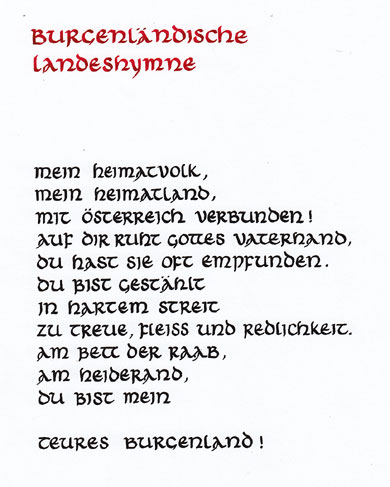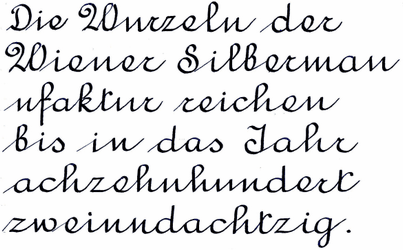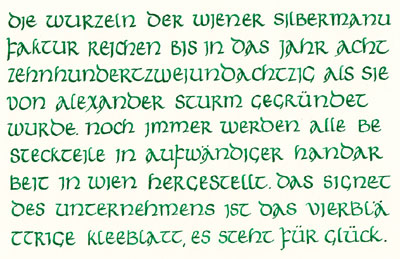
| Das Layout,
also der Gesamteindruck einer Seite, eines Plakates oder einer
Webseite, umfasst das Zusammenwirken von Text und Abbildungen. Die Typografie hingegen widmet sich nur den Textelementen, vom Buchstaben über das Wort, die Zeile und den Satz bis zum Textblock. Großbuchstaben (=Versalien) und Kleinbuchstaben (=Gemeine oder Minuskeln) werden mit bestimmten Abständen (=Laufweite) aneinander gereiht. Bei zu geringen Buchstabenabständen ist der Text schlecht lesbar, sind die Abstände zu groß, wirkt der Text löchrig: Hier ist die Laufweite zu klein, die Lesbarkeit beeinträchtigt. Hier ist die Laufweite zu groß, der Text überdehnt. |
| Kommen Buchstaben nebeneinander zu
stehen, die wegen ihrer Form große Freiräume entstehen lassen, sieht
das erstens nicht gut aus und beeinträchtigt zweitens den Lesefluss. Diese "problematischen" Buchstaben sind die Großbuchstaben A L T V W und die Kleinbuchstaben f j r v w y. Beim Wort SPALTE ist das "Loch" zwischen den Zeichen L und T gut erkennbar, aber auch der viel kleinere Freiraum zwischen dem P und dem A fällt unangenehm auf. Wird der Abstand zwischen P und A bzw. zwischen L und T reduziert, sieht die Sache schon viel besser aus: SPALTE darunter zum Vergleich das ursprüngliche Wortbild: SPALTE |
Inserat der Zeitschrift HANDEL 19. 12. 2011 |
Typo von WIEN ENERGIE |
DER NEUE CITROËN C3
Inserat im KURIER (13. Jänner
2017)
Das smart electric bike. Inserat 52. Woche 2012 |
Inserat von T-Mobile "Topkombi". 10. 6. 13 in HEUTE |
Plakatbilder WEBSCHOOL |
Inserat der Welser Herbstmesse 2016
BILLA-Inserat (HEUTE 8. 10. 2019)
WIENER ZEITUNG Titelseite (12. 10. 2019)
Bild: Frey REWE-LKW 6. Juli 2022
XXXLutz-Kampagne 7. August 2026
| In den 1930er Jahren haben runde Schriftarten die gebrochenen verdrängt. Runde Schriften sind leichter zu schreiben und deutlich besser zu lesen. | |
GEBROCHENE SCHRIFTARTEN Beispiele |
RUNDE SCHRIFTARTEN Beispiele |
Fraktur
Die folgenden Schriftartenbeispiele wurden von RENATE FREY geschrieben:
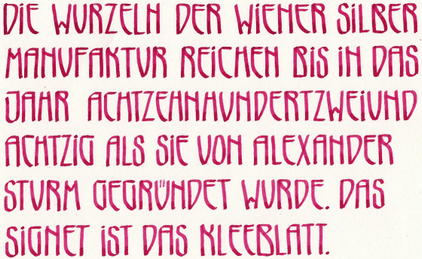
UNZIALE
Bild links
(Geschrieben mit: Online Bestwriter 0.8)
JUGENDSTIL
Bild rechts (Geschrieben mit: Online
Bestwriter 1.4)
RUNDSCHRIFT
Bild links
(Geschrieben mit: Online Bestwriter
1.4)
KURSIV
Bild rechts (Geschrieben mit:
Online Bestwriter 1.4)
ENGLISCHE SCHREIBSCHRIFT
Bild links (Geschrieben mit:
Spitzfeder)
VORFRAKTUR Bild
rechts (Geschrieben mit: Pilot 2.4)
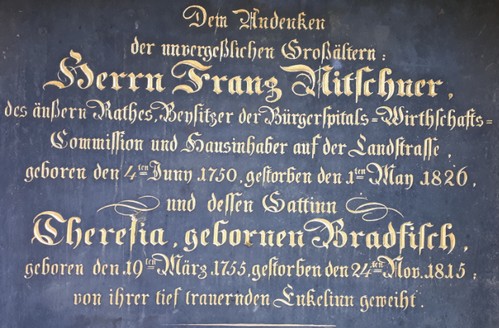
Biedermeier (Friedhof Sankt Marx - Wien)
Unziale
Jugendstil Bild
| Die Größe des Wortzwischenraums entspricht - abhängig von der typografischen Philosophie - der Breite des Buchstabens i oder der Punze (= Innenraum) des Buchstabens n. | |
| Bei den Schriften gibt es welche mit Serifen (das sind die häkchenförmigen Enden), Courier New zum Beispiel und solche ohne: Verdana. |
| Schriften ohne "Füßchen" laden nicht zum Lesen ein, daher sind Bücher mit literarischen Texten immer mit Serifenschriften gedruckt. | |
| Alt + gut.
Ein Meilenstein: Baskerville (1754) Die weltweit meistverwendete Schrift ist die Unternehmen, die Helvetia verwenden (Zeitungen: Guardian, Hürriyet; American Airlines, Panasonic, Schweizer Bundesbahn, ...):
Jünger (1898), aber auch schon ein Klassiker, die Akzidenz-Grotesk:
Über drei Jahrzehnte verwendete der Schweizer Grafiker Celestino Piatti diese Schrift bei der Gestaltung der Umschlagseiten der dtv-Buchreihe. Abb. rechts oben
Die schlichten Schriftschnitte wecken so viel
Faszination, dass ein Film über sie gedreht wurde und das Museum of Modern
Art (MoMA) in New York die Helvetica 2007 zum 50. Geburtstag in einer
Ausstellung würdigte. Der Grafiker und Verleger Lars Müller nennt sie auch
«das Parfum der Stadt», denn sie ist an fast jeder Straßenecke dieser Welt
anzutreffen. Er hat der Helvetica 2002 einen Band gewidmet mit dem
Untertitel «Homage to a Typeface».
Ebenfalls 2009 veröffentlichte der Schriftendesigner
Erik Faulhaber die
Aeonis, eine serifenlose, auf das für die Lesbarkeit Notwendigste
reduzierte Schrift. Beim versalen Eine Schrift, die ihre Heimatstadt verkörpert
wollten die Berliner Hannes von Döhren und Livius Dietzel schaffen.
Ergebnis war die ITC Chino:
Akiro Kobayashi,
künstlerischer Leiter von Linotype, gewann Adrian
Frutiger, um dessen nach ihm benannten Klassiker, die "Frutiger"
zu modifizieren: (alt - neu) Tern (Trans European
Road Network) wurde für eine bessere Lesbarkeit von Verkehrswegweisern im
Rahmen eines EU-Projekts (In-Safety) am
Inserat in der
NZZ-Sonderbeilage vom 9. 4. 2014
Inserat in der
Kronen Zeitung vom 16. 5. 2014
WK-Inserat in HEUTE
vom 19. 5. 2015 (TOURISMUSZONEN)
LIDL-Flugblatt 13. 7. 2023
Nur auf den ersten Blick ein Fisch